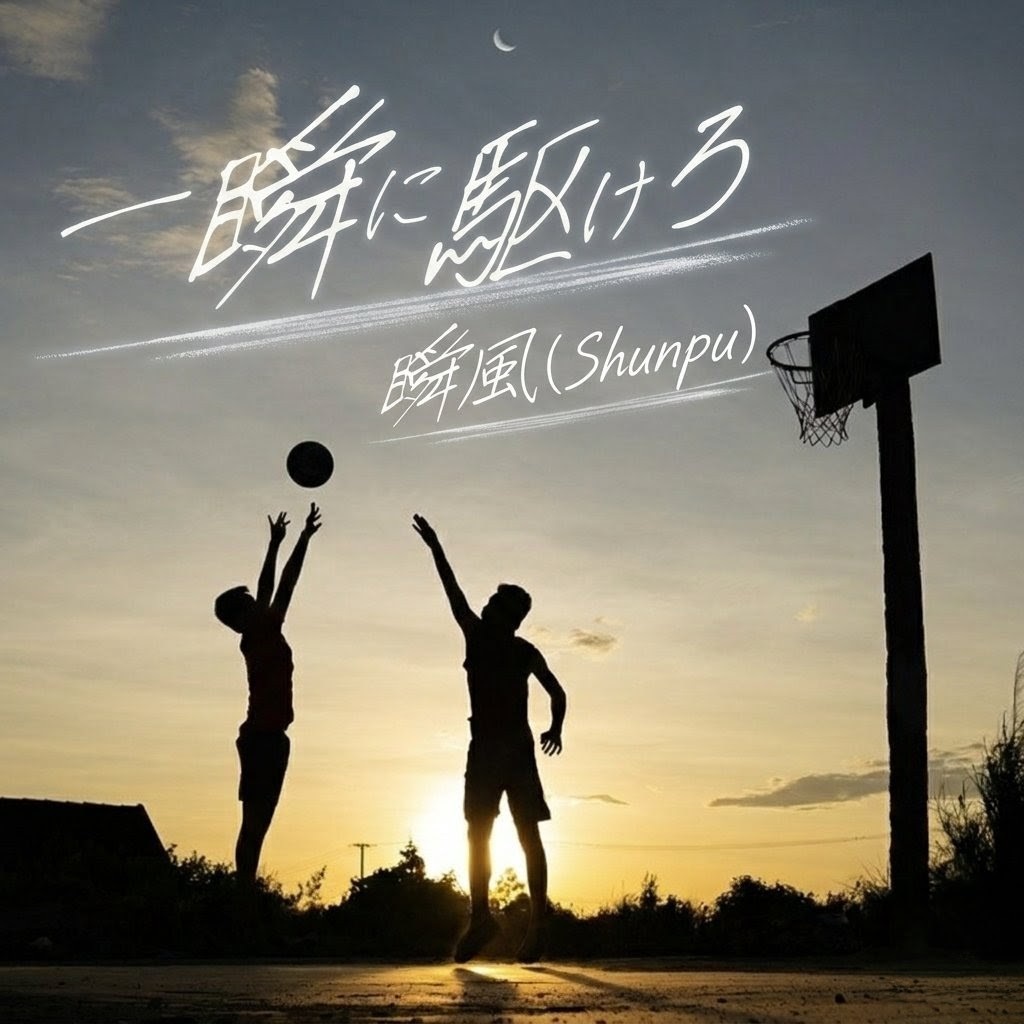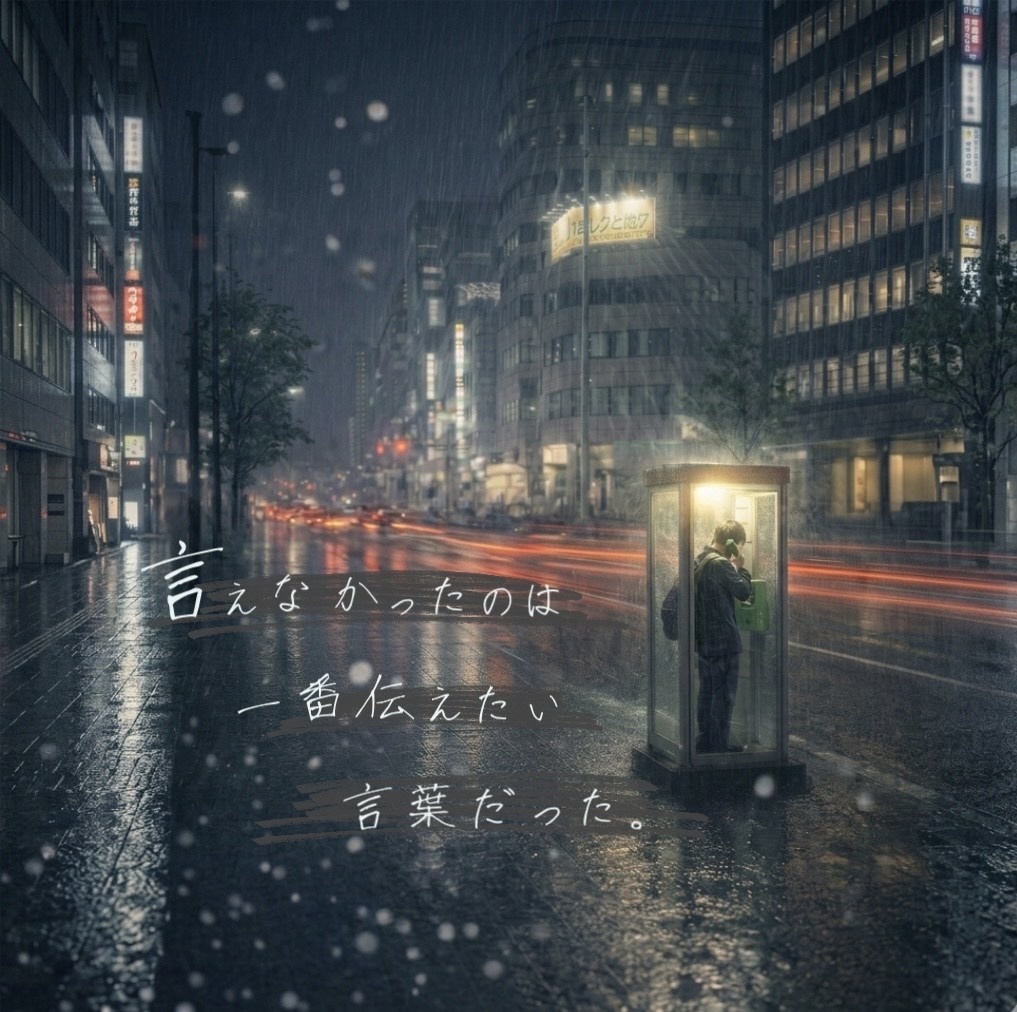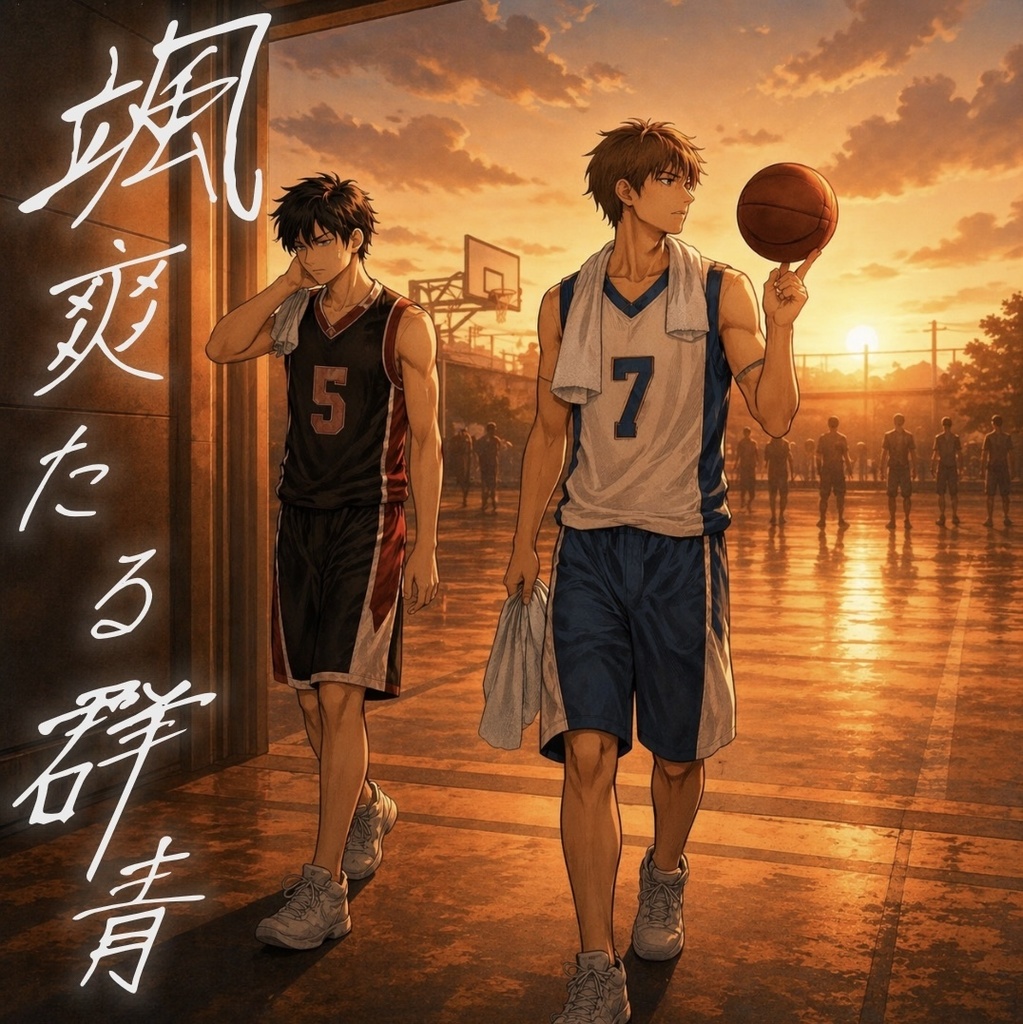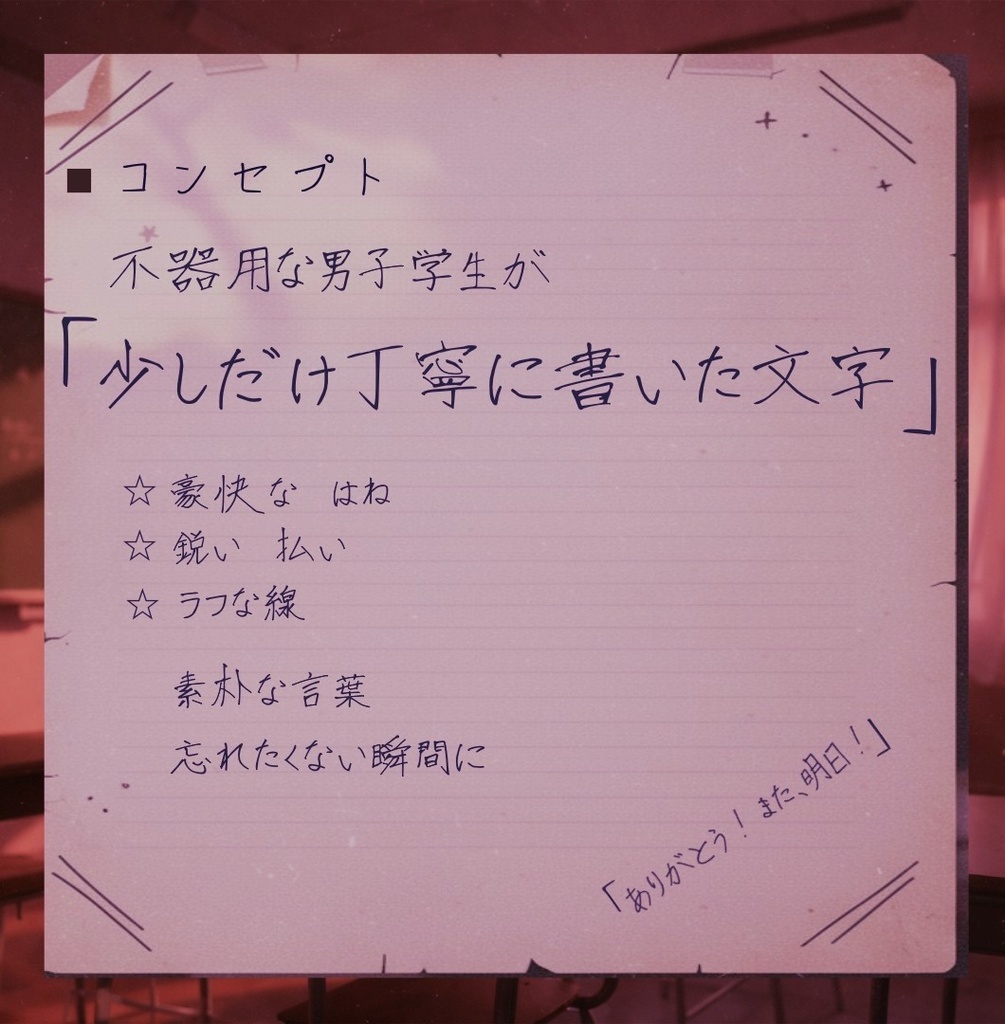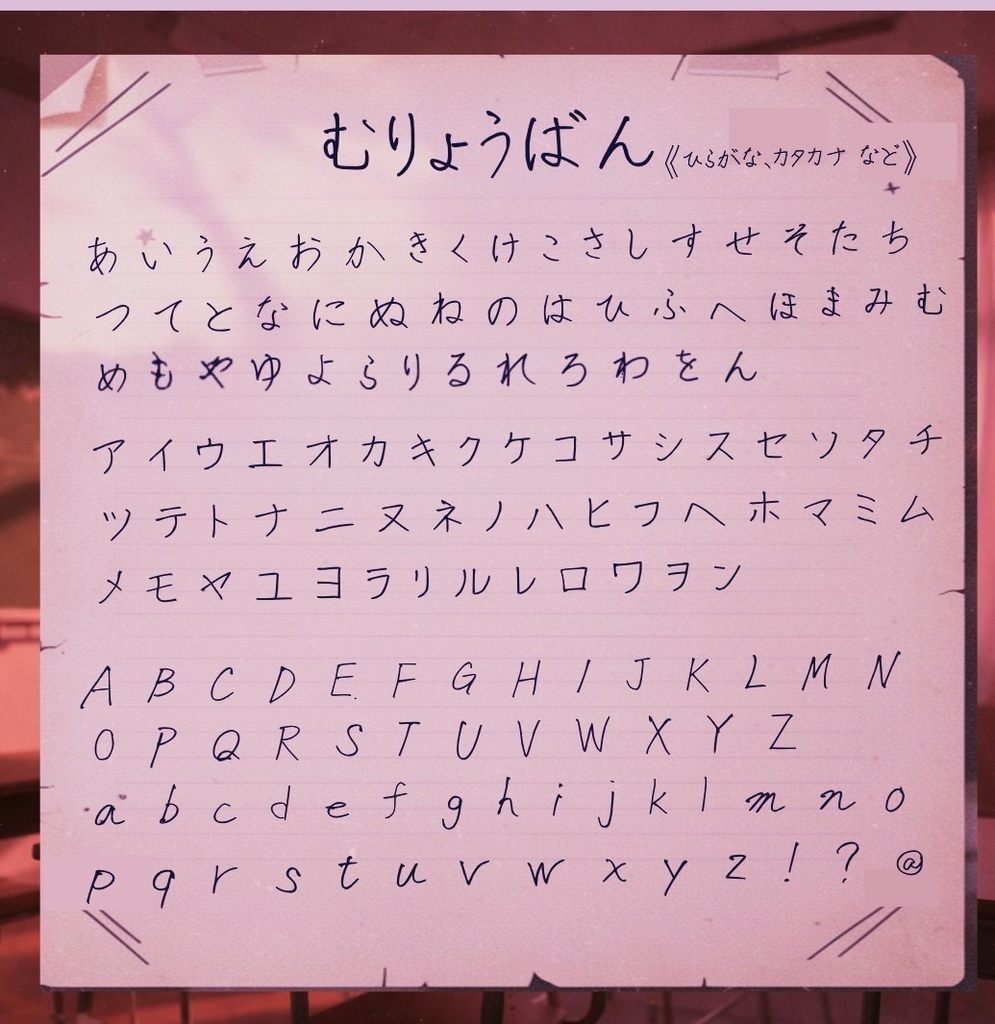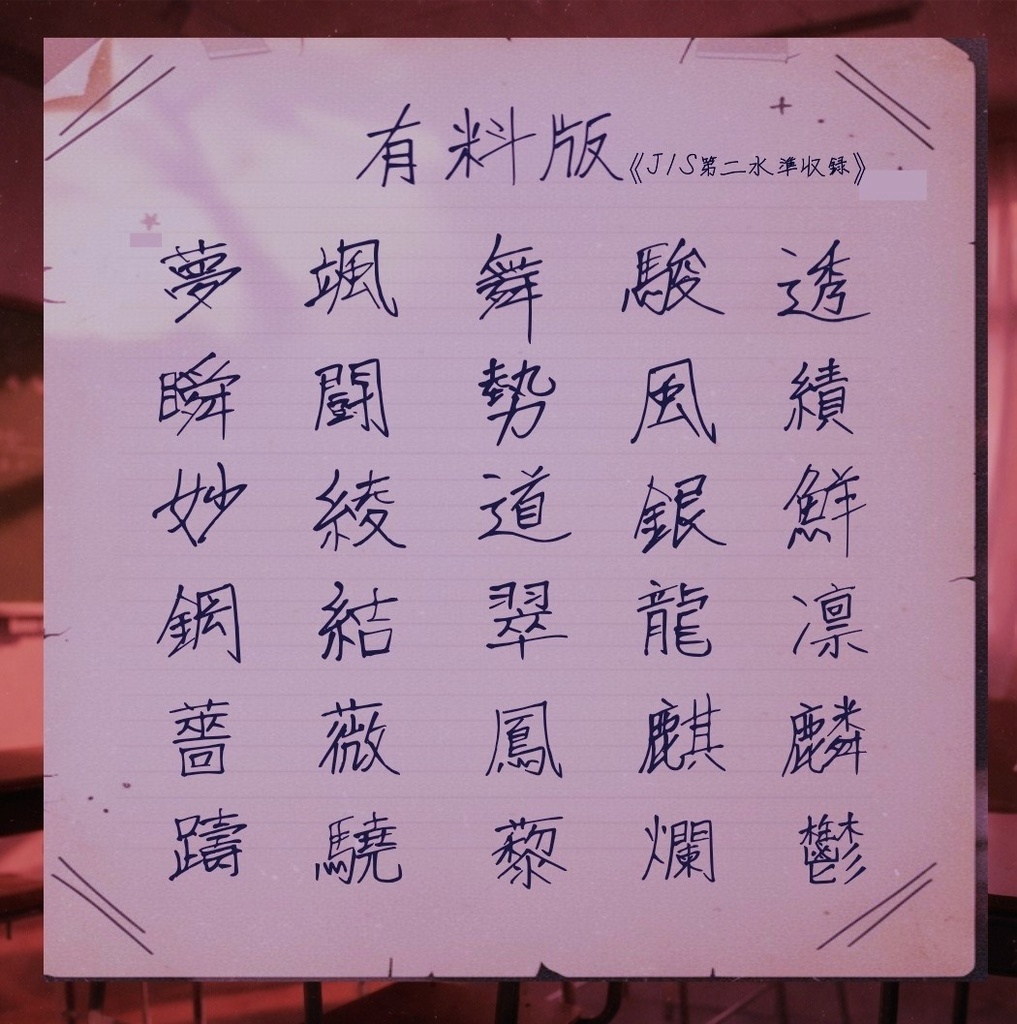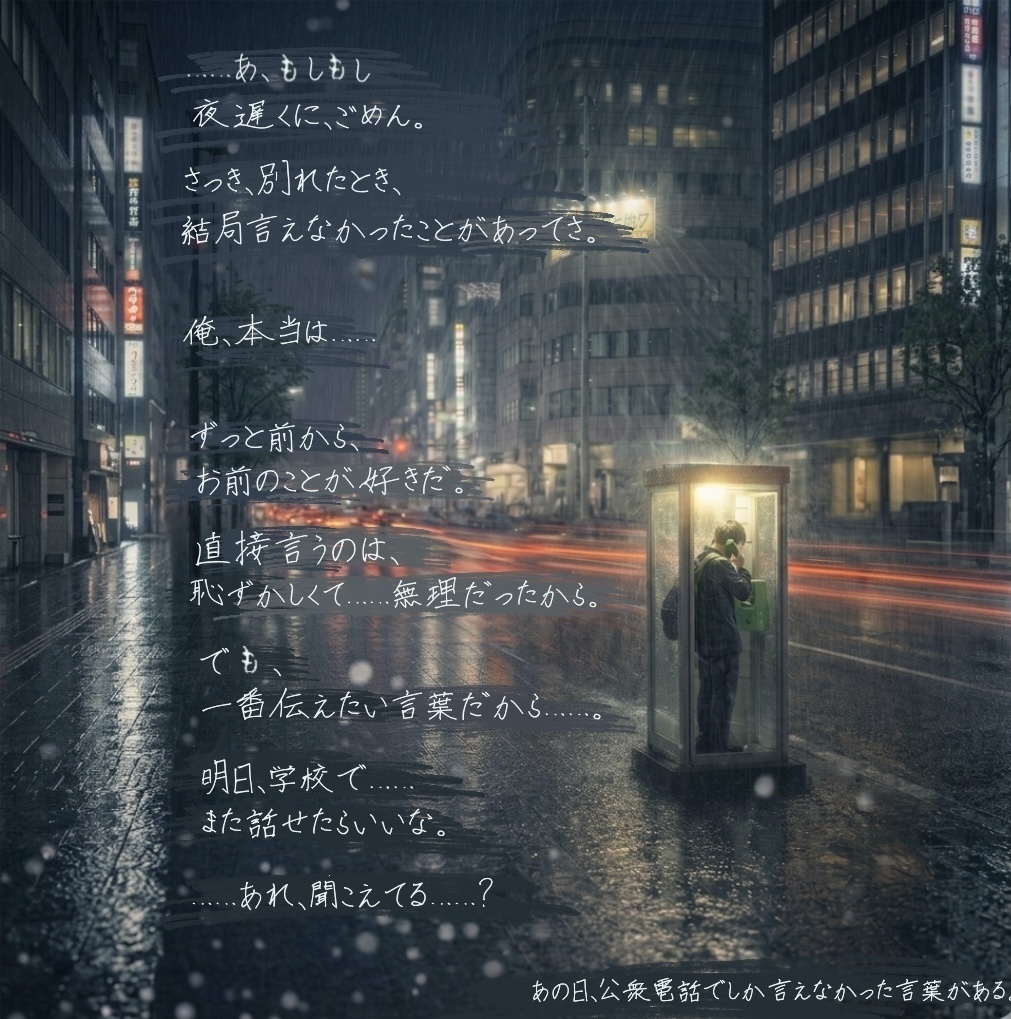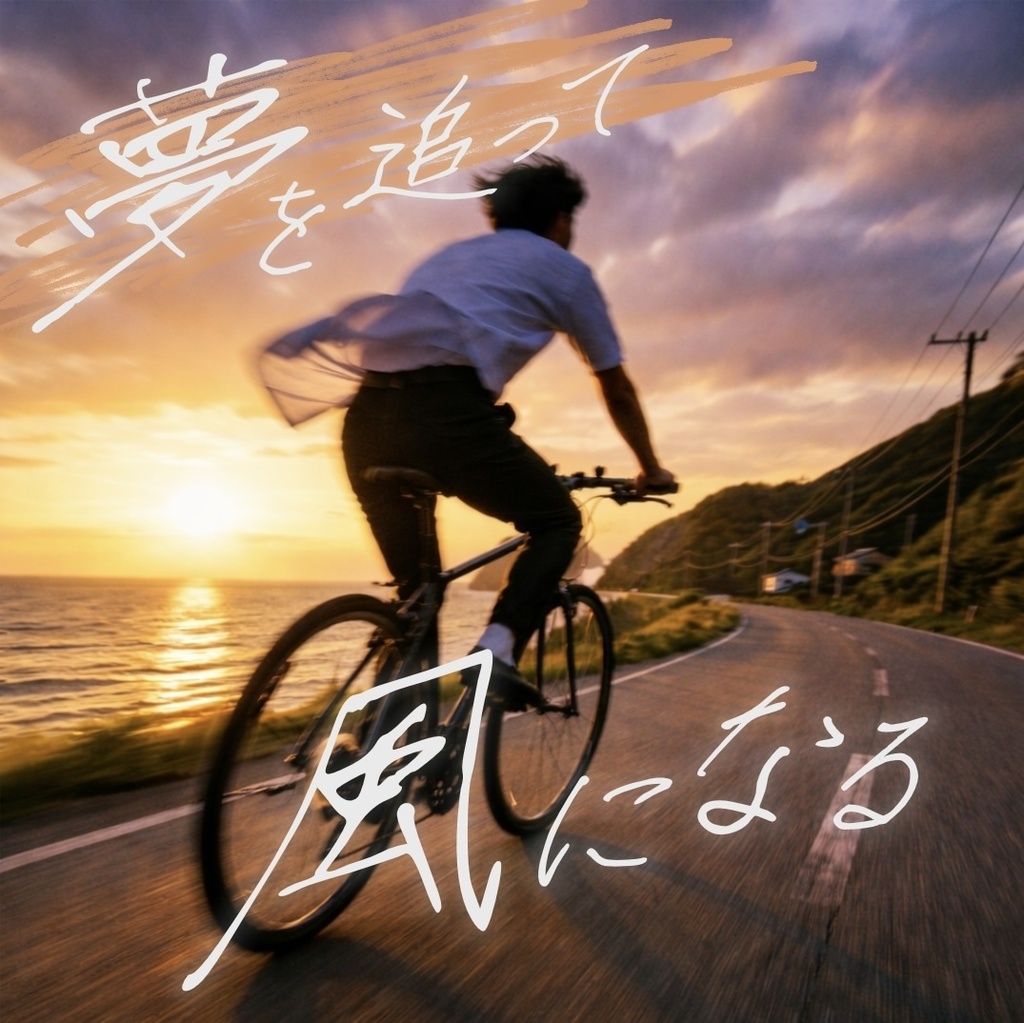
【商用可/無料版有】手書きフォント「瞬風 shunpu」【6,865文字】
■コンセプト 不器用な男子学生が、少しだけ丁寧に書いた文字。 豪快に跳ねる払いと、ラフな線のゆらぎが特長の手書きフォントです。 手書きならではの温度と、人の気配を感じる文字です。 特に漢字は、強めの筆圧と大胆なはね・払いによって、 どこか男らしい勢いを感じる仕上がりです。 ■ 特徴 ・大胆なはね・払いで、動きのある文字表現 ・ラフさと可読性のバランス ・大画面でもプロポーションが崩れない、 なめらかな曲線設計 ・一般的な手書きフォントとは異なる少し古風な雰囲気 ・青春やスポーツの熱量と相性の良いデザイン ■ 有料版について JIS第二水準までの漢字(6,865文字)をすべて収録。 難解な言い回しも可能な為、機微な感情や複雑な情景を存分に表現出来ます。 ■ 利用シーン ・青春の一瞬を切り取る表現に ・気持ちを込めたメッセージに ・整った字では伝わりにくい、心のつぶやきに ■ おきさまで 累計ダウンロード数が6,000を越えました。 又、多くの方から推薦を頂きました。ありがとうございます。 ・いいフォント様で紹介 https://goodfreefonts.com/9741/ ・フロップデザイン様のX投稿で紹介 24万インプレッション / 6000いいね https://x.com/i/status/2029733511410897228 ・日本語フリーフォント様で紹介 https://ffont.jp/shunpu/ ・コリス様で紹介 https://coliss.com/articles/freebies/japanese-free-fonts.html ■ 最後に 少し不器用で、まっすぐな文字を。 作品の空気を変える一本になれたら嬉しいです。